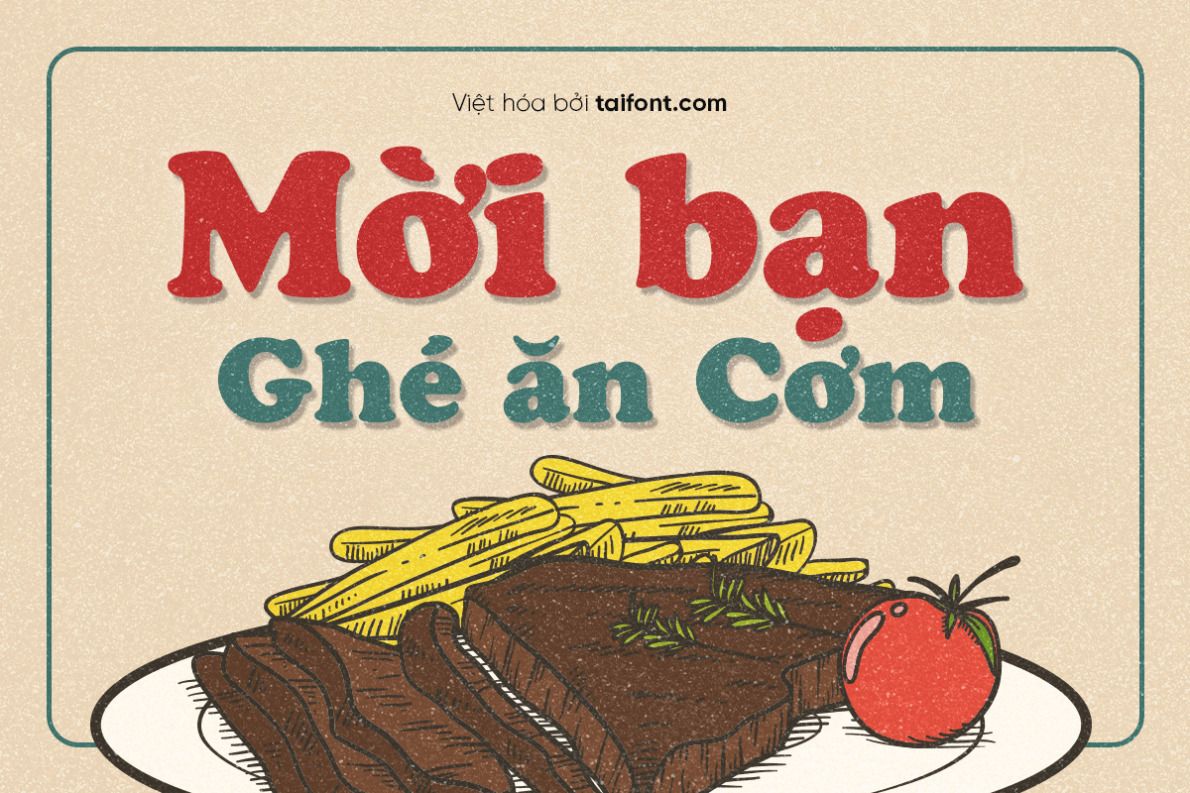
Font Ẩm Thực Miễn Phí: Font UTM Cooper
Font Ẩm Thực Miễn Phí: Font UTM Cooper – Tuyệt vời cho các ẩn phẩm thiết kế ẩm thực
Bạn đang tìm kiếm một font chữ phù hợp cho những thiết kế liên quan đến ẩm thực? Font UTM Cooper chính là sự lựa chọn lý tưởng cho bạn! Được thiết kế và Việt hóa bởi Đinh Kiên – một tên tuổi lâu năm trong lĩnh vực Việt hóa font chữ, UTM Cooper nhanh chóng trở thành font kinh điển được ưa chuộng trong ngành thiết kế.
Điều Nổi Bật Về Font UTM Cooper
UTM Cooper không chỉ đơn thuần là một font chữ; nó là một biểu tượng được sử dụng rộng rãi trong các thiết kế đồ họa, đặc biệt là trong lĩnh vực ẩm thực. Đường nét mềm mại, thanh thoát của font chữ này giúp tạo nên sự hấp dẫn và thu hút cho các sản phẩm thiết kế, đặc biệt là khi áp dụng cho các banner, menu hay tạp chí về món ăn truyền thống Việt Nam.
Ứng Dụng Đa Dạng Trong Thiết Kế Ẩm Thực
UTM Cooper rất phù hợp để sử dụng trong các thiết kế sau:
- Banner Quảng Cáo Món Ăn: Font chữ này giúp nâng cao giá trị của hình ảnh và thông tin trên các banner quảng cáo, làm nổi bật các món ăn truyền thống Việt Nam một cách ấn tượng.
- Menu Nhà Hàng: Với thiết kế thân thiện và dễ đọc, UTM Cooper là một lựa chọn tuyệt vời cho menu nhà hàng, giúp thực khách dễ dàng nhận diện cũng như cảm nhận được sự tinh tế trong từng món ăn.
- Tạp Chí Ẩm Thực: Font chữ này cũng được nhiều nhà thiết kế lựa chọn cho các bài viết và tiêu đề trong tạp chí ẩm thực, mang đến vẻ đẹp chuyên nghiệp và nghệ thuật cho các ấn phẩm.
Tại Sao UTM Cooper Lại Được Yêu Thích?
Một lý do chính khiến UTM Cooper trở thành font chữ được đông đảo người làm thiết kế ưa chuộng là sự hòa quyện giữa tính thẩm mỹ và chức năng. Đường nét mềm mại và khả năng truyền tải cảm xúc của font chữ này giúp tạo ra một môi trường đọc thoải mái, ấn tượng cho người tiêu dùng. Hơn nữa, với tính chất miễn phí, UTM Cooper dễ dàng tiếp cận đối với mọi loại hình thiết kế.
Kết Luận
Nếu bạn đang tìm kiếm một font chữ ẩm thực miễn phí nhưng chất lượng, UTM Cooper chính là sự lựa chọn tuyệt vời cho bạn. Hãy thử nghiệm và cảm nhận những gì mà font chữ này mang lại cho các thiết kế của bạn. Với UTM Cooper, bạn không chỉ đầu tư vào một font chữ, mà còn đầu tư vào nghệ thuật và sự sáng tạo của riêng mình trong lĩnh vực ẩm thực.